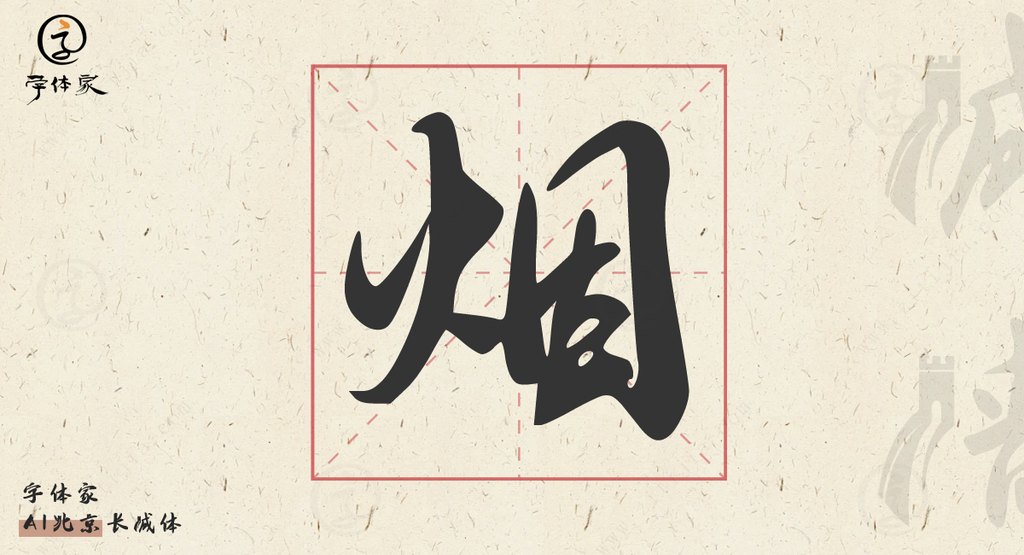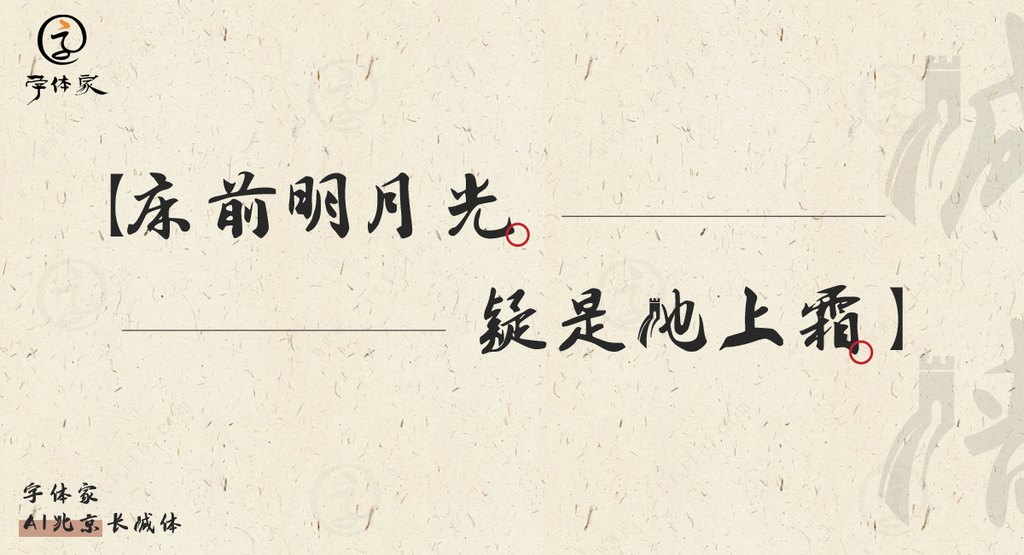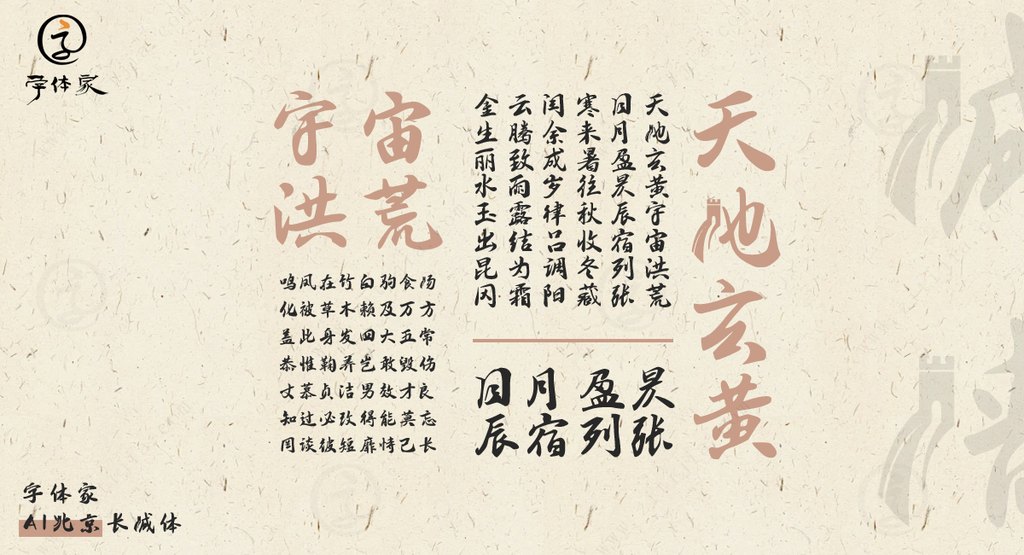
字体家AI神笔造字:北京长城体点亮现代设计
字体家AI推出的北京长城体:传统与现代的完美结合
字体家AI神笔造字又有新作为,这次将中华文明的象征——长城,融入到字体设计中,创造了别具一格的北京长城体。这款艺术字体,以其独特的笔画设计,仿佛将长城的雄伟壮丽凝聚于字里行间。
设计灵感
北京长城体的灵感源于延续千年的长城,它抵御外敌的历史,横亘于山脉之中的宏伟造型,使得长城成为中华文化的象征。设计师巧妙地将长城的图案元素融入到字体的笔画中,实现了书法文字与长城的完美融合。
应用场景
这种字体非常适合用于广告标题、平面文案、海报标题和网页广告。无论是在现代时尚的广告设计中,还是在富有文化底蕴的活动展示中,北京长城体都能为作品增添一种厚重的历史感和艺术性。